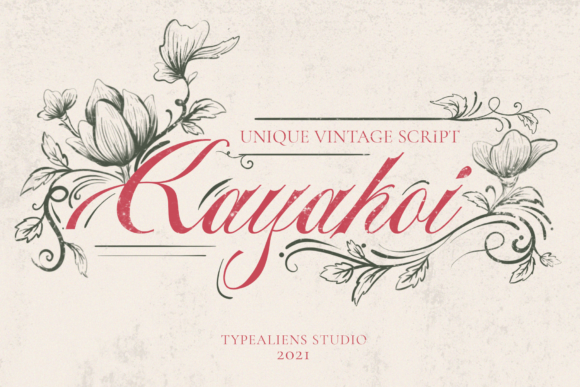
Creativefabrica Kayakoi Font 2021
[Creativefabrica] Kayakoi Font (2021)
Каякои - это элегантный и винтажный, выглядящий как рукописный шрифт, который излучает изысканность и элегантность.
Его стильные чередования и лигатуры делают этот шрифт идеальным для любого проекта.